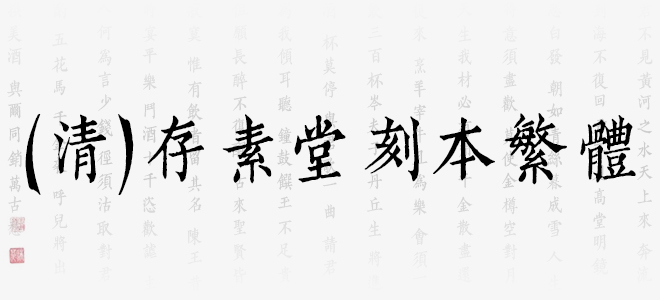
(清)存素堂刻本繁體以清代存素堂刻本為藍(lán)本運(yùn)用軟件制作而成,筆畫流暢飛揚(yáng),結(jié)體左緊右松,開合對(duì)比強(qiáng)烈,進(jìn)一步強(qiáng)化了動(dòng)感。整套字體有如一氣呵成,行筆迅捷華麗,其個(gè)性浪漫灑脫,適用于現(xiàn)代詩(shī)歌、短文的排版,以及文化、商業(yè)類品牌的廣告語(yǔ)設(shè)計(jì)。歡迎喜歡(清)存素堂刻本繁體字體的朋友前來(lái)下載使用。
(清)存素堂刻本繁體